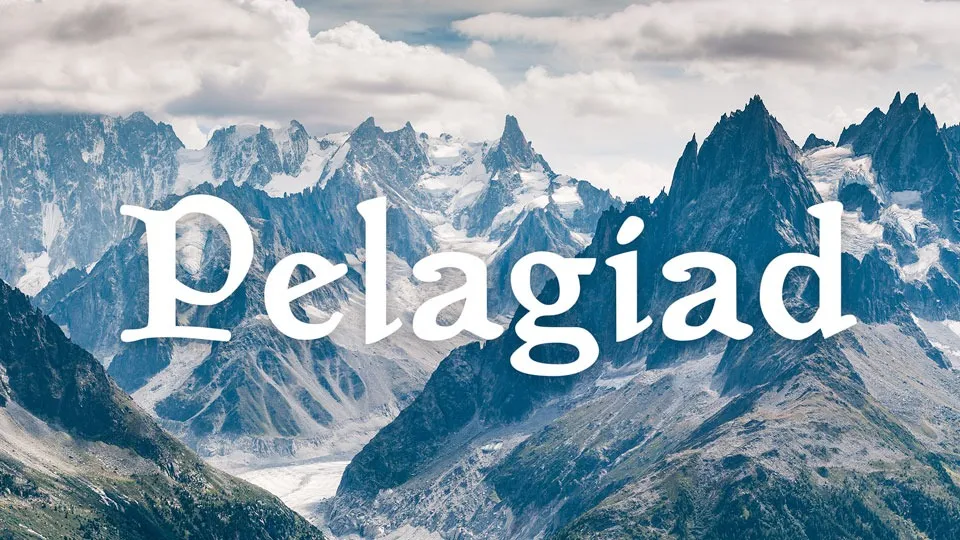
A Pelagiad Font é uma elegante fónta serif que se adequa perfeitamente a fins leisier ou turismo. Inspirada nos cartões mágicos e EF Medieva, ela é perfeita para expressar elegância no ambiente de jogo de mesa aberto, mas também serve como fonte poderosa em uma variedade de ambientes digitais. Este recurso gráfico multilingue contém letras maiúsculas e minúsculas, números e símbolos, suportando linguas diversificadas. Como um complemento para o OpenMW game engine, a Pelagiad é também uma fonte versátil que atende necessidades variadas, desde design gráfico até criação de sites ou aplicativos web.